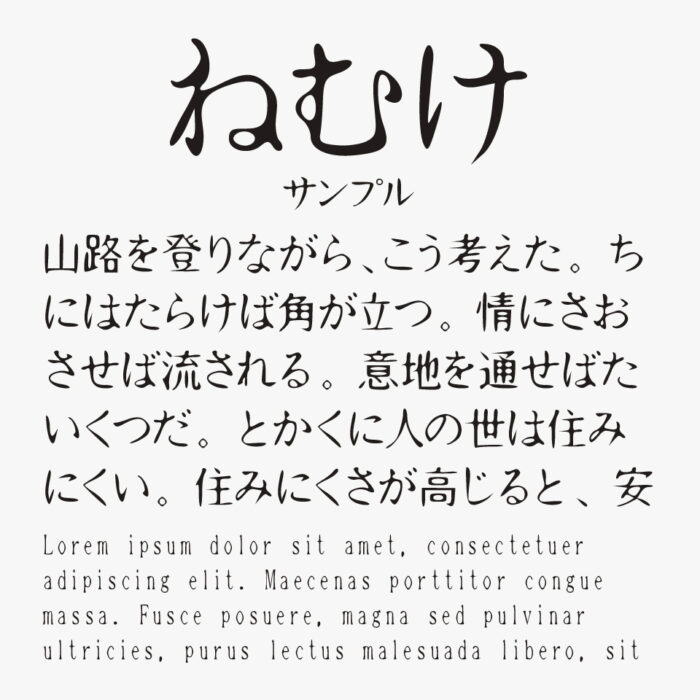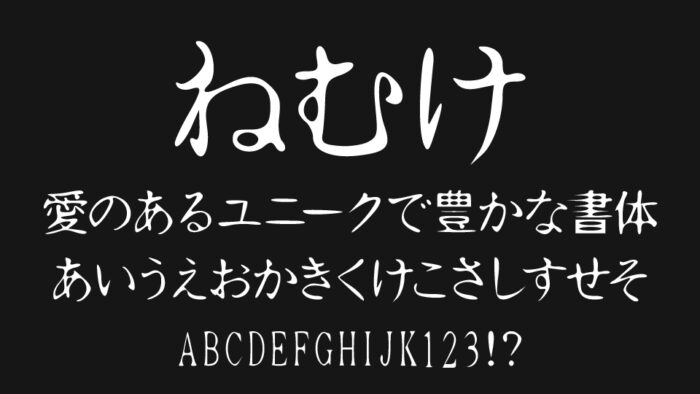
ねむけフォント(Nemuke)は、ゆるやかな曲線が眠たげで脱力感のあるユニークな明朝体フォントです。
力を抜いた脱力感があり、文字にゆらぎのある文字形が独特のリズムを生み出し、見た人の眠気を誘うような面白さが感じられるフォントです。
脱力感のある表現やホラーやミステリーな雰囲気にもぴったりなフォントです。